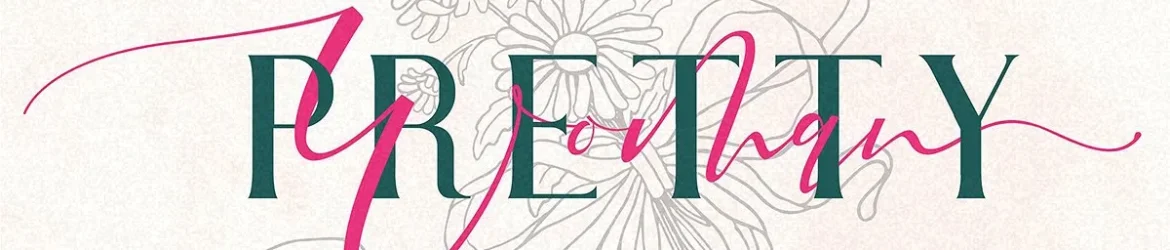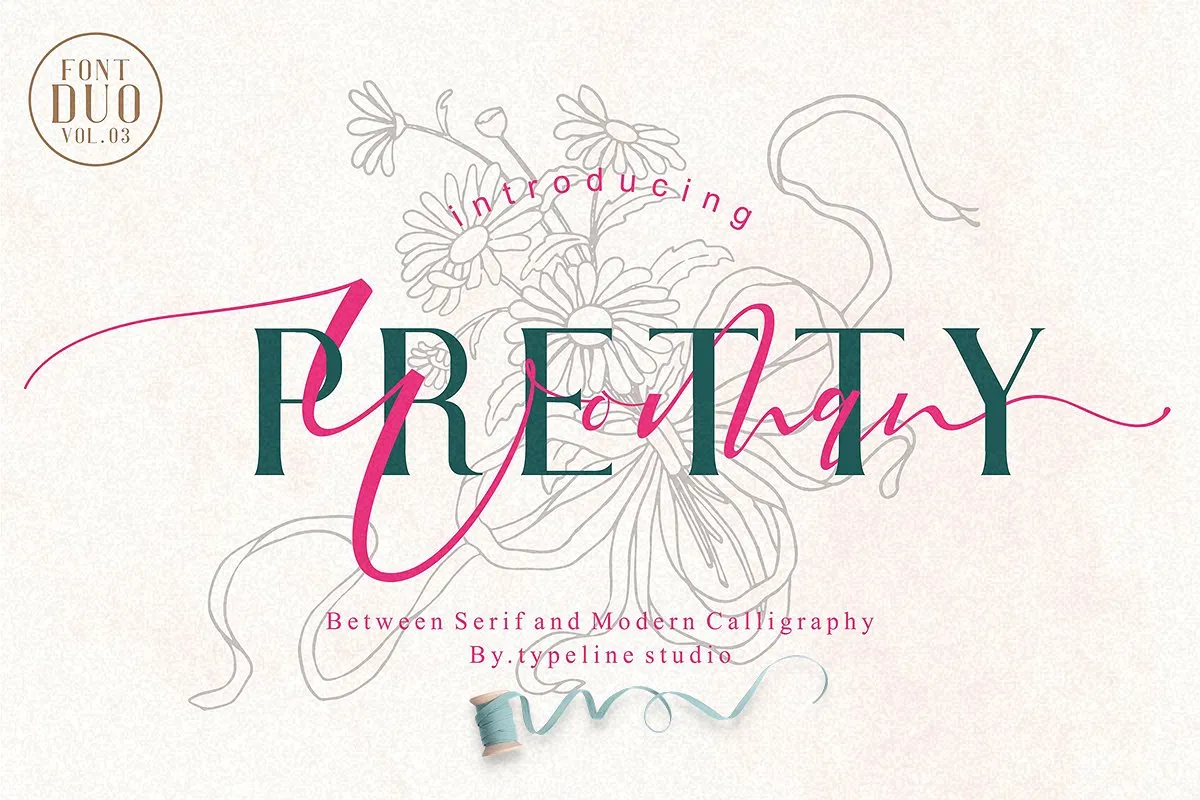
Pretty Woman Font Duo – Fonte Grátis
Pretty Woman Font Duo
A Pretty Woman Font Duo é uma nova opção para quem busca estilo e sofisticação em sua tipografia. Este duo de tipo serif e script combina perfeitamente a elegância clássica dos caracteres serif com um toque moderno de escrita moderna, criando um conjunto único ideal para criar declarações marcantes e decorar qualquer design. Seja para criações de marca, convites de casamento, textos do tipo de noivado, citações ou até mesmo uma revista – essa fonte é flexível o suficiente para atender a uma variedade de necessidades. Com certeza, Pretty Woman é um excelente adorno que adicionará estilo ao seu projeto, transformando-o em algo realmente especial e memorável. Seja você criador de material publicitário ou designer gráfico, essa fonte será definitivamente o toque final perfeito para seus trabalhos.